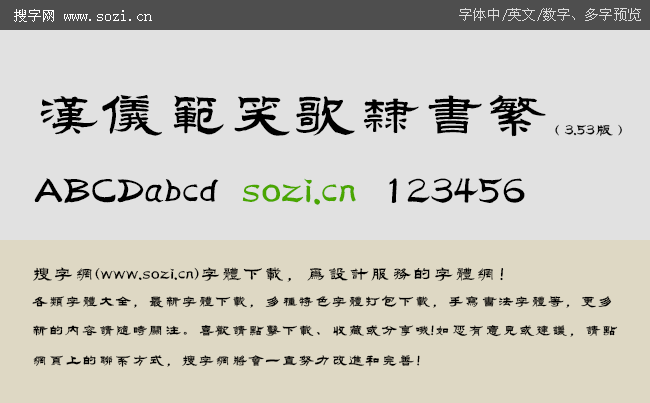
漢儀范笑歌隸書(shū)繁
搜字網(wǎng)給大家提供一款有古典風(fēng)味的漢儀范笑歌隸書(shū)繁體下載。范笑歌隸書(shū)具有魏碑的筆畫(huà)筆意,并有篆書(shū)的韻味風(fēng)格,其中的范橫畫(huà)是范體隸書(shū)特有獨(dú)創(chuàng)的筆畫(huà),如同舒展的雙翅,使隸書(shū)中的蠶頭燕尾更張揚(yáng),更有力度。范橫畫(huà)改變了千百年來(lái)隸書(shū)的蠶頭燕尾的程式寫(xiě)法,整個(gè)字體風(fēng)格剛?cè)嵯酀?jì),瀟灑舒展,具有很強(qiáng)的裝飾性。此款字體適用于書(shū)籍、畫(huà)報(bào)的主副標(biāo)題和個(gè)性品牌設(shè)計(jì)推廣等環(huán)境。